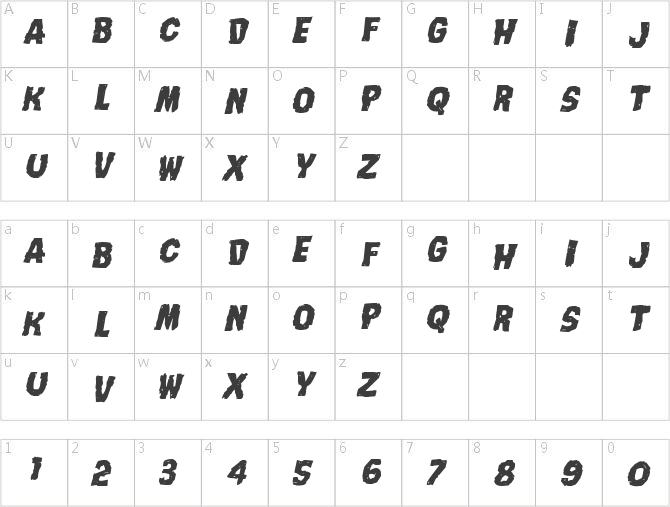
nightmarealleyexpandital
nightmarealleyexpandital介紹
nightmarealleyexpandital字體字庫是一款讓人賞心悅目、百看不厭的英文字體,適合各類廣告和產品包裝設計應用,字體大小0.14MB,格式為ttf字體,上傳用戶是M_墨董,作者/版權方為未知